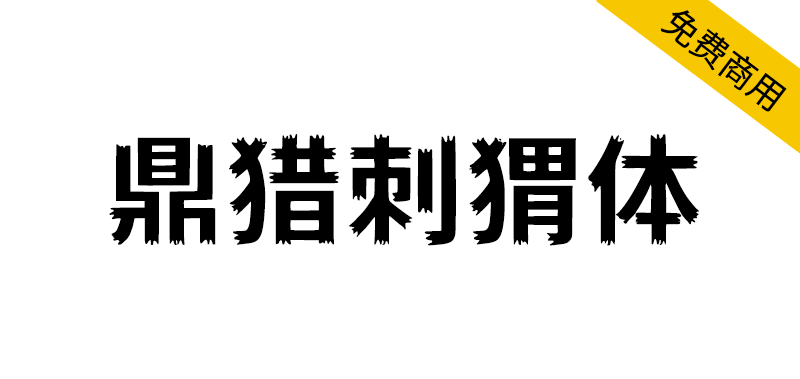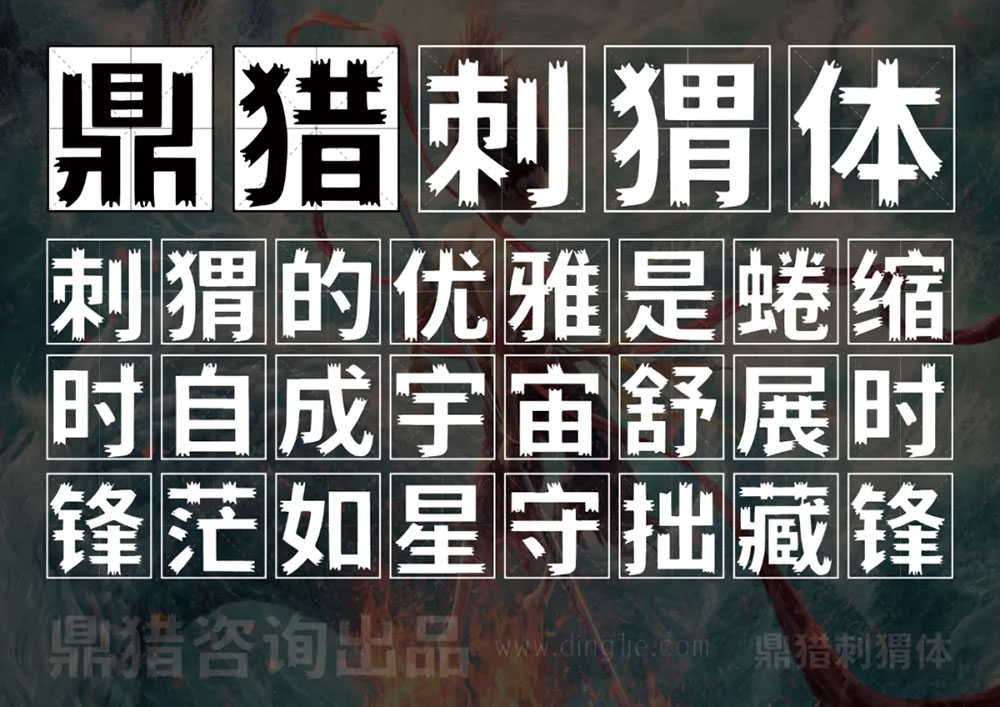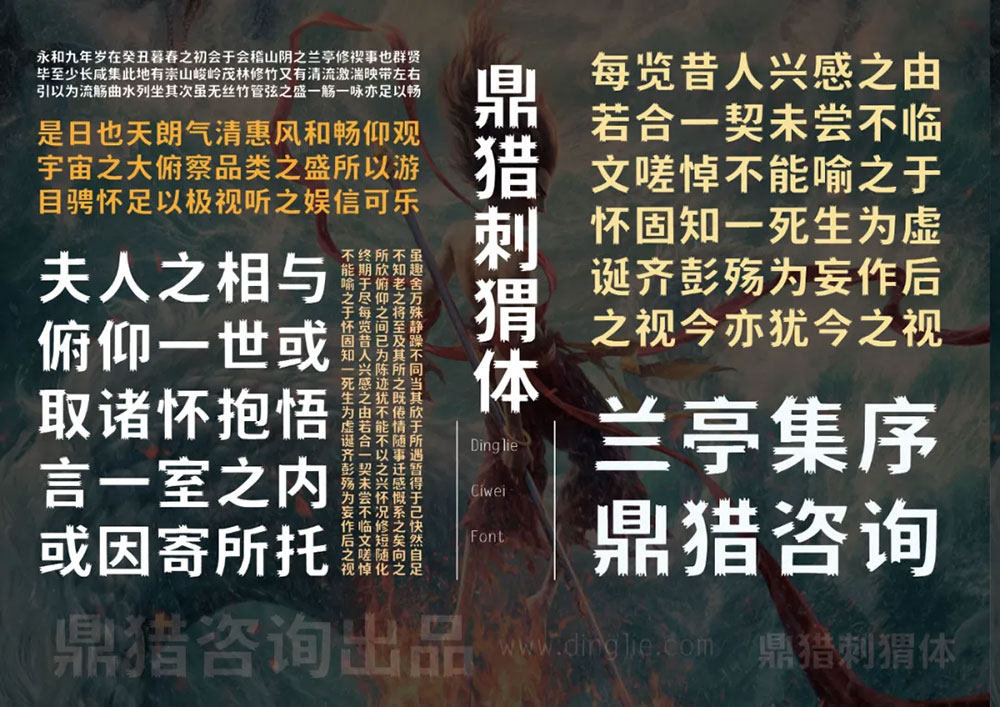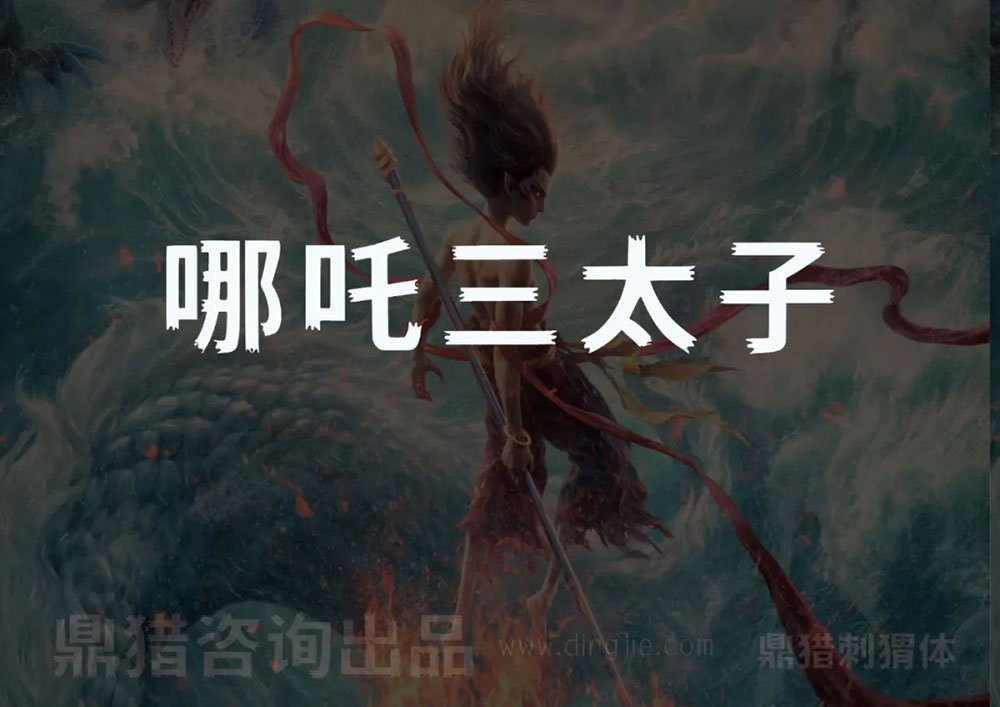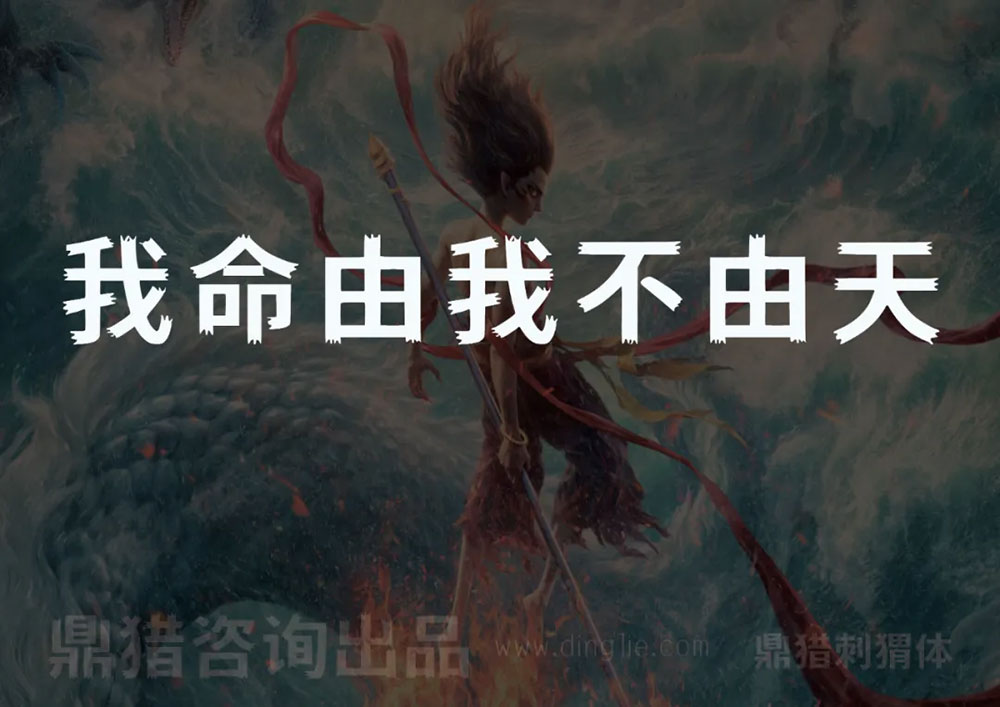
鼎猎刺猬体,是一款以黑体为蓝本衍化的创意字体,整体有撕裂的锯齿状边缘,有稳健和善良的内在,却有着棱角和锋芒,像是刺猬,有锋芒而不失柔软的善良和坚强的意志。很像仍在火热上映《哪吒2》的魔丸哪吒。鼎猎刺猬体适合美食餐饮、展会展览、企业文化,以及报刊封面、餐饮茶饮、美妆护肤等各个行业。踏入2025年,鼎猎将持续推出更多字体。
考虑到字体应尽可能满足各类型的姓和名,鼎猎刺猬体以简体中文汉字编码国家标准(GB2312编码)为标准,共计设计了多达7415个字符,其中汉字6769个。可以满足绝大部分印刷设计等要求。